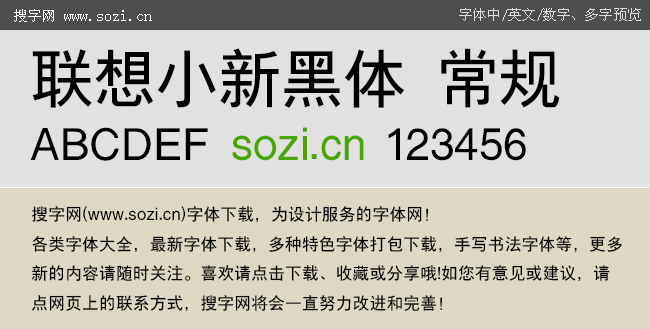
聯(lián)想小新黑體 常規(guī)
搜字網(wǎng)給大家提供一款聯(lián)想小新黑體 常規(guī)中文字體下載,聯(lián)想小新黑體常規(guī)體是以簡約的筆畫、精簡的線條、柔和的弧度,打造出的一款人文與科技交織的黑體字,平直極簡的橫豎筆畫,突顯品牌的科技感、未來感。常規(guī)體中筆畫粗細(xì)的微弱差距,營造良好的視覺穩(wěn)定性。適合標(biāo)題設(shè)計、網(wǎng)頁設(shè)計、海報設(shè)計、包裝設(shè)計等應(yīng)用。